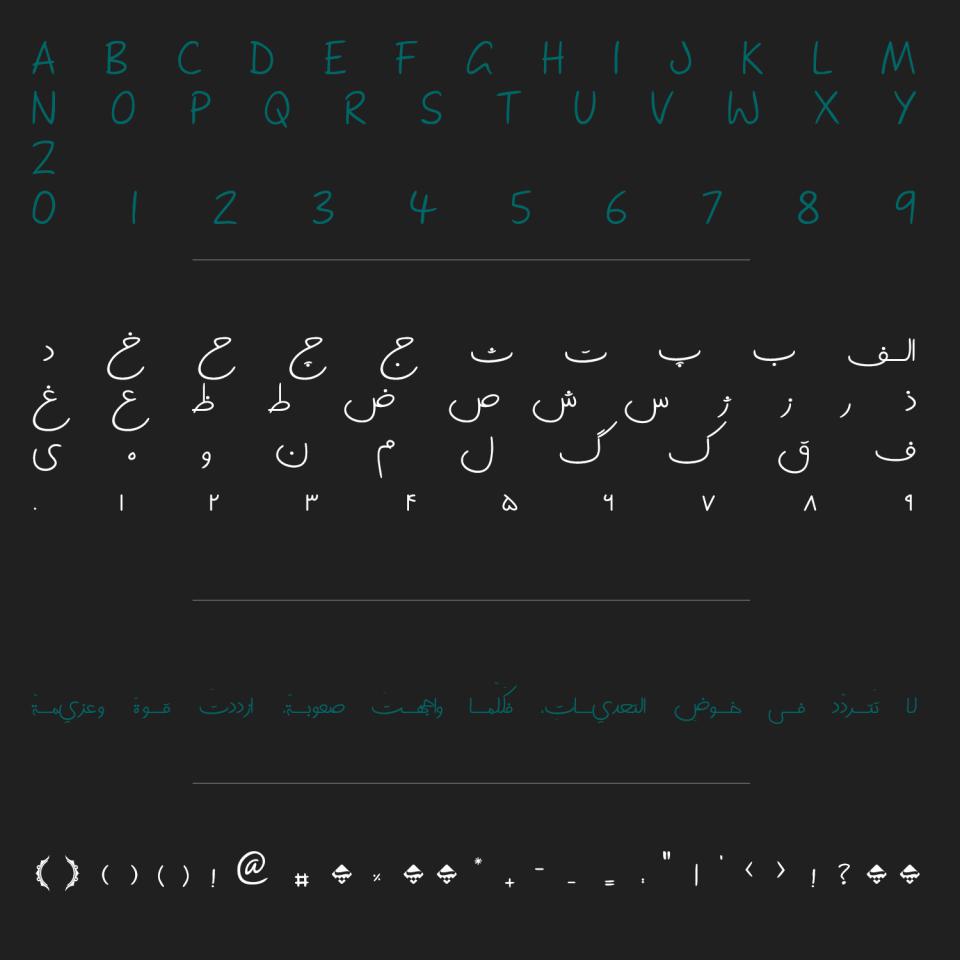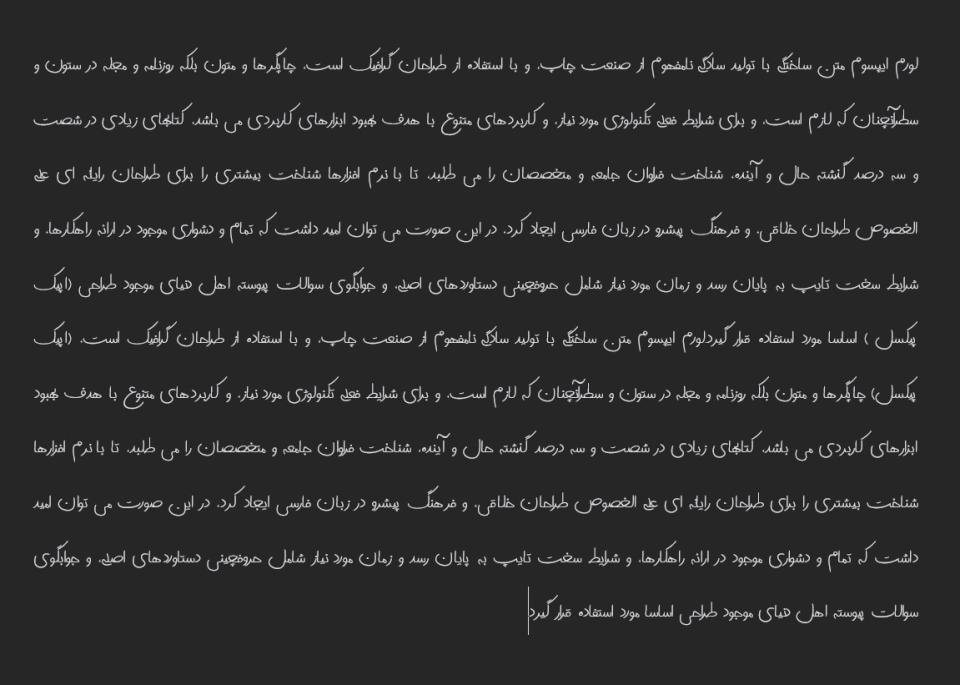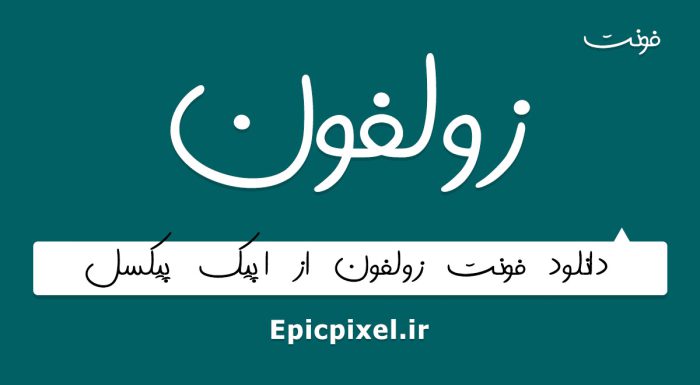
فونت زلفون فارسی
فونت دست نویس زلفون، یه انتخاب خاص برای کساییه که دنبال یه حس دست نویس واقعی تو طراحی هاشون هستن. این فونت با ظرافت خاصی طراحی شده و حس نوشتن با خودکار رو به خوبی منتقل می کنه. حروفش یه جورایی طراحی شدن که انگار واقعا یه نفر با دست خط خودش نوشته، این ویژگی به طرح های شما یه صمیمیت و حس شخصی می بخشه که تو فونت های دیگه کمتر پیدا می شه.
یکی از ویژگی های خوب زلفون، خوانایی بالای اونه، با وجود اینکه ظاهرش دست نویسه، اما به راحتی می شه متن ها رو خوند. این یعنی هم می تونید تو طراحی های گرافیکی ازش استفاده کنید و هم تو متن های طولانی تر. البته یه نکته هم هست، شاید زلفون برای متن های خیلی رسمی یا علمی چندان مناسب نباشه، چون ذاتش یه حس خودمونی و دوستانه داره.
این فونت به خوبی از زبان فارسی پشتیبانی می کنه و تمام حروف و علائم لازم رو داره. این یعنی خیالتون راحته که تو هر پروژه ای می تونید ازش استفاده کنید. در کل، اگه دنبال یه فونت دست نویس با حس واقعی و خوانایی بالا هستید که به طرح هاتون یه جلوه خاص بده، زلفون یه انتخاب عالیه. این فونت رایگانه و به راحتی می تونید دانلودش کنید و تو پروژه هاتون ازش لذت ببرید.